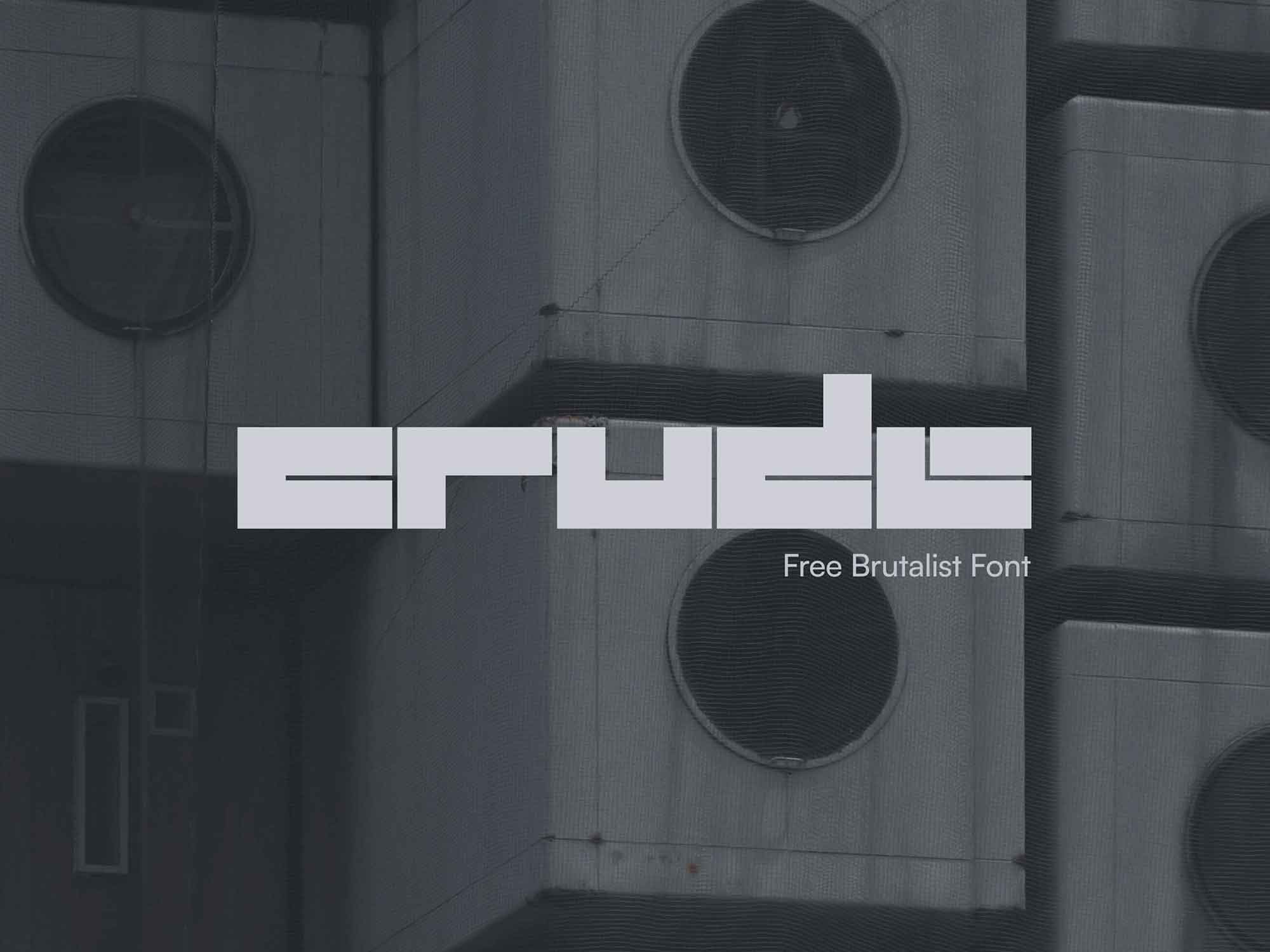
Crude Display Font – Download Grátis
A fonte Crude é um design de exibição construído com blocos geométricos grossos que dão uma aparência pesada e bold. Suas linhas verticais e horizontais definidas se tornam atraentes e arquitetônicas, traduzindo a beleza desses designs em letras e números em 2D. Com todos os caracteres essenciais que incluem números, pontuação, letras maiúsculas e minúsculas, a fonte é perfeitamente adequada para uso em cabeçalhos de publicações como revistas e jornais. Ela também pode ser integrada em websites, aplicativos móveis e mídias sociais. Esta fonte oferece uma aparência robusta e atraente que combina perfeitamente com os estilos modernos e minimalistas, tornando-a uma escolha ideal para quem busca um efeito forte em seus projetos.